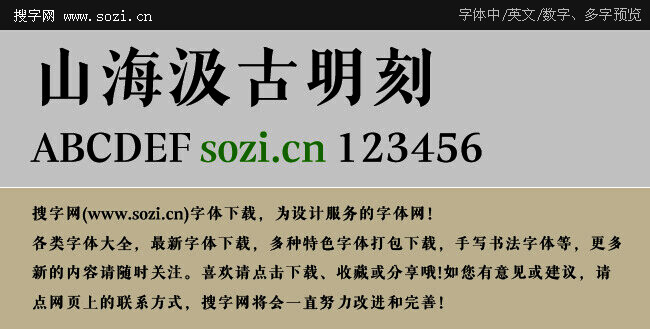
山海汲古明刻
搜字網(wǎng)提供一款山海汲古明刻中文藝術字體下載,山海汲古明刻是一款國風復古刻本字體,包含簡體漢字6763個,字形秉承中國明代古籍善本之字形特性,版刻刀法剔透,字形方正,端莊嚴謹,古樸大方,起落頓筆有棱角。在飽有筆墨之意的同時,又突顯刀刻之鋒美,筆刀結合剛柔并濟。在秉承筆形間創(chuàng)新,結合當代設計視覺環(huán)境,融入現(xiàn)代審美,適用場景更多元,筆畫造型清晰銳利,刪繁取簡,筆鋒凌厲,速度感強,粗細對比強烈,重現(xiàn)刀刻古韻之美。適合包裝設計、海報設計、廣告設計等應用。